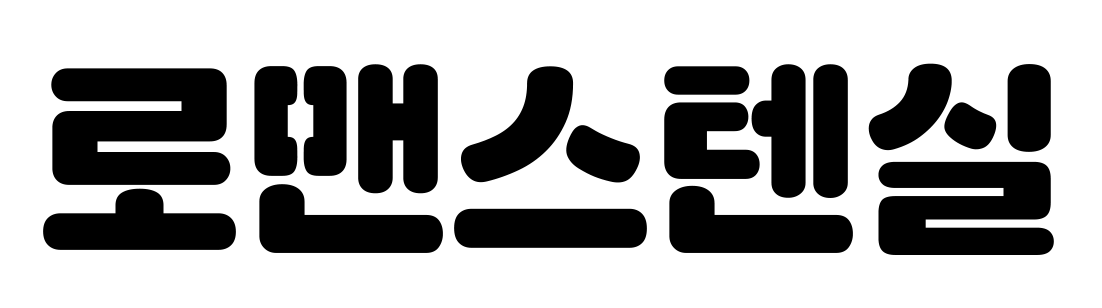
Sandoll 로맨스텐실
산돌 로맨스텐실은 자소를 오려내 공간을 채우는 스텐실 기법을 적용한 산돌의 두 번째 스텐실 폰트다.
앞서 출시 된 액션스텐실이 딱딱하고 날카로운 이미지라면, 로맨스텐실은 획의 시작과 마감, 잘라낸 단면 모두 곡선으로 표현해 전체적으로 둥글고 발랄한 이미지를 갖고 있다.
주로 제목이나 강조하고 싶은 부분에 사용하면 효과적이며, Basic과 Outline을 함께 활용할 경우 색다른 느낌을 줄 수도 있다.